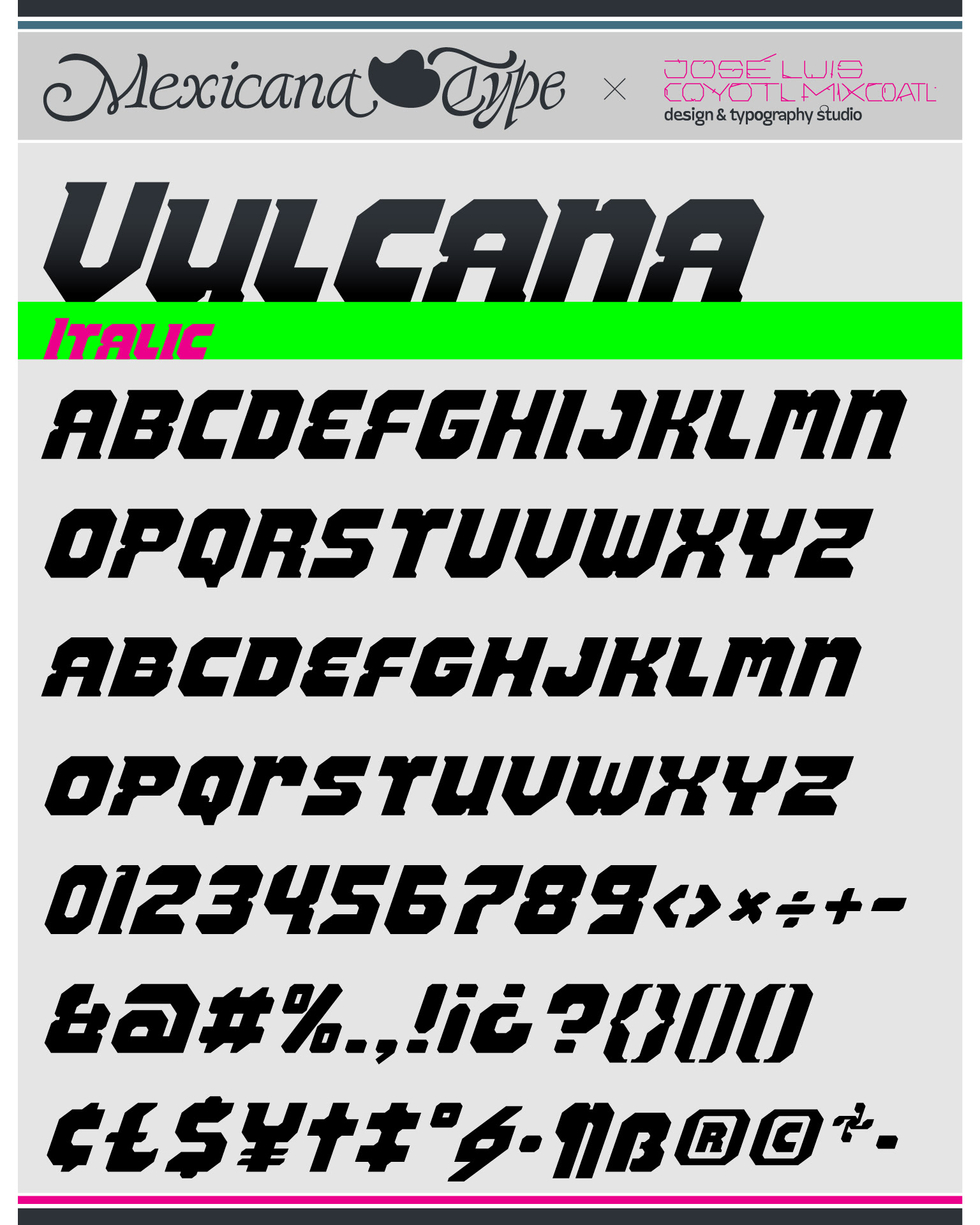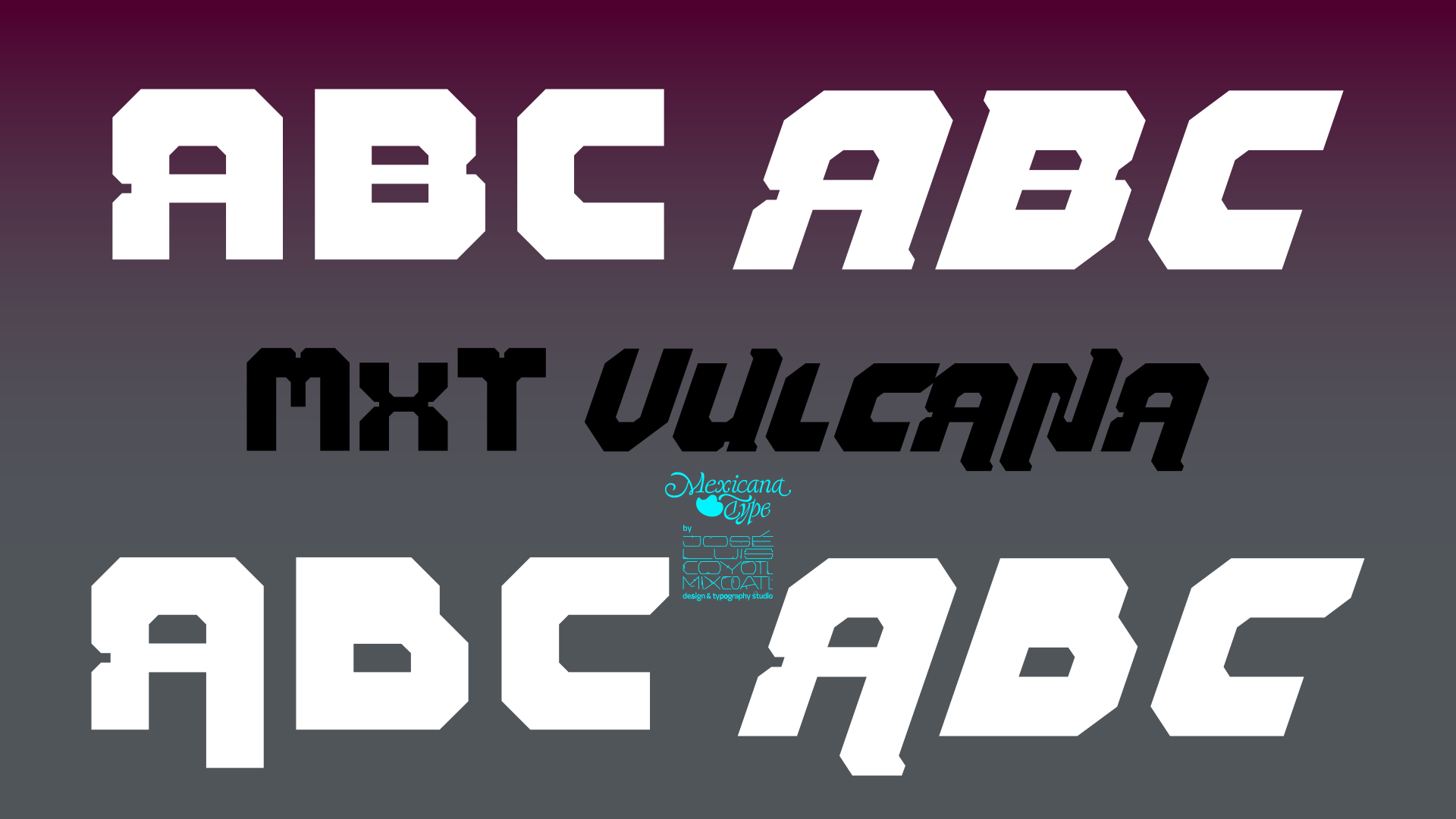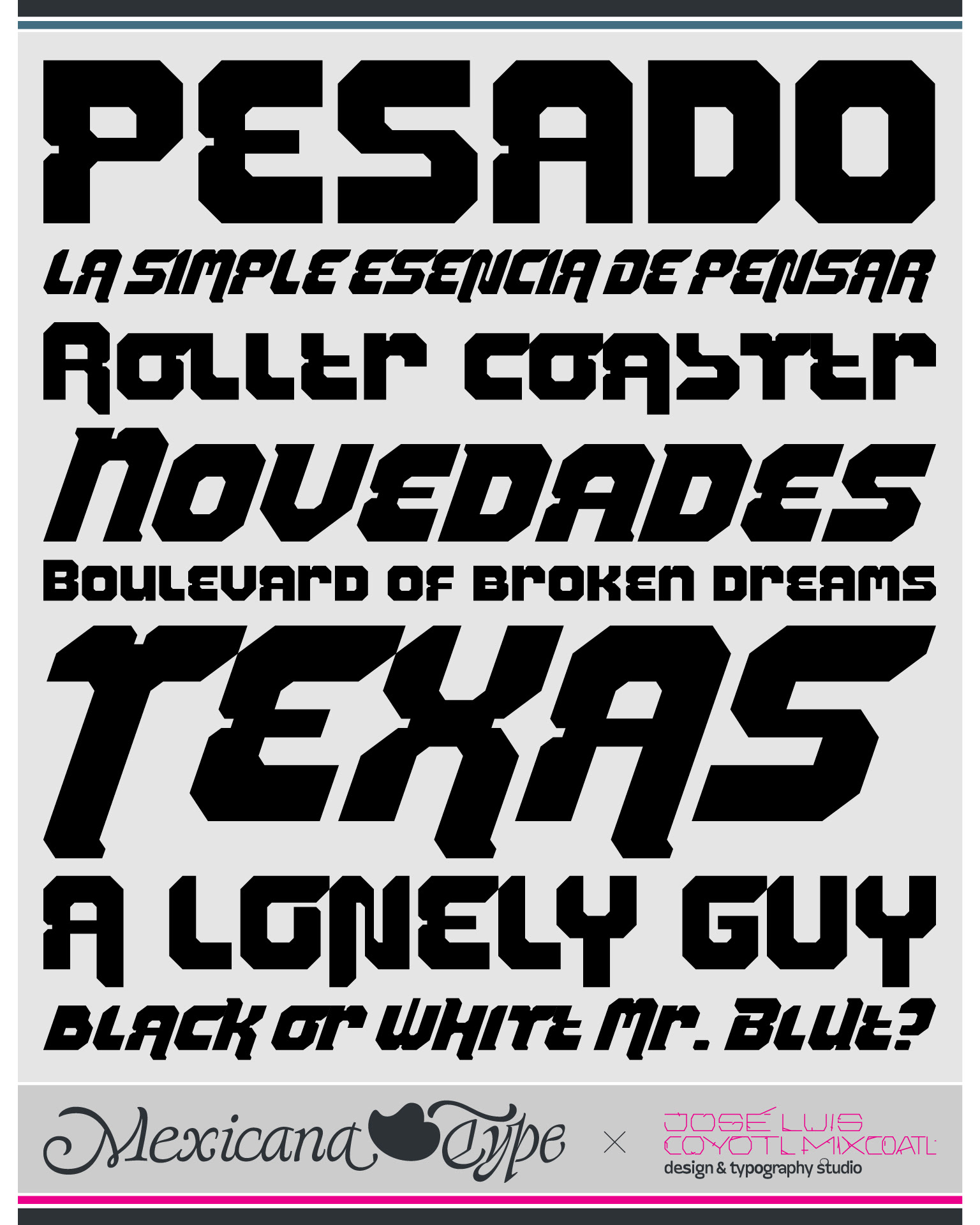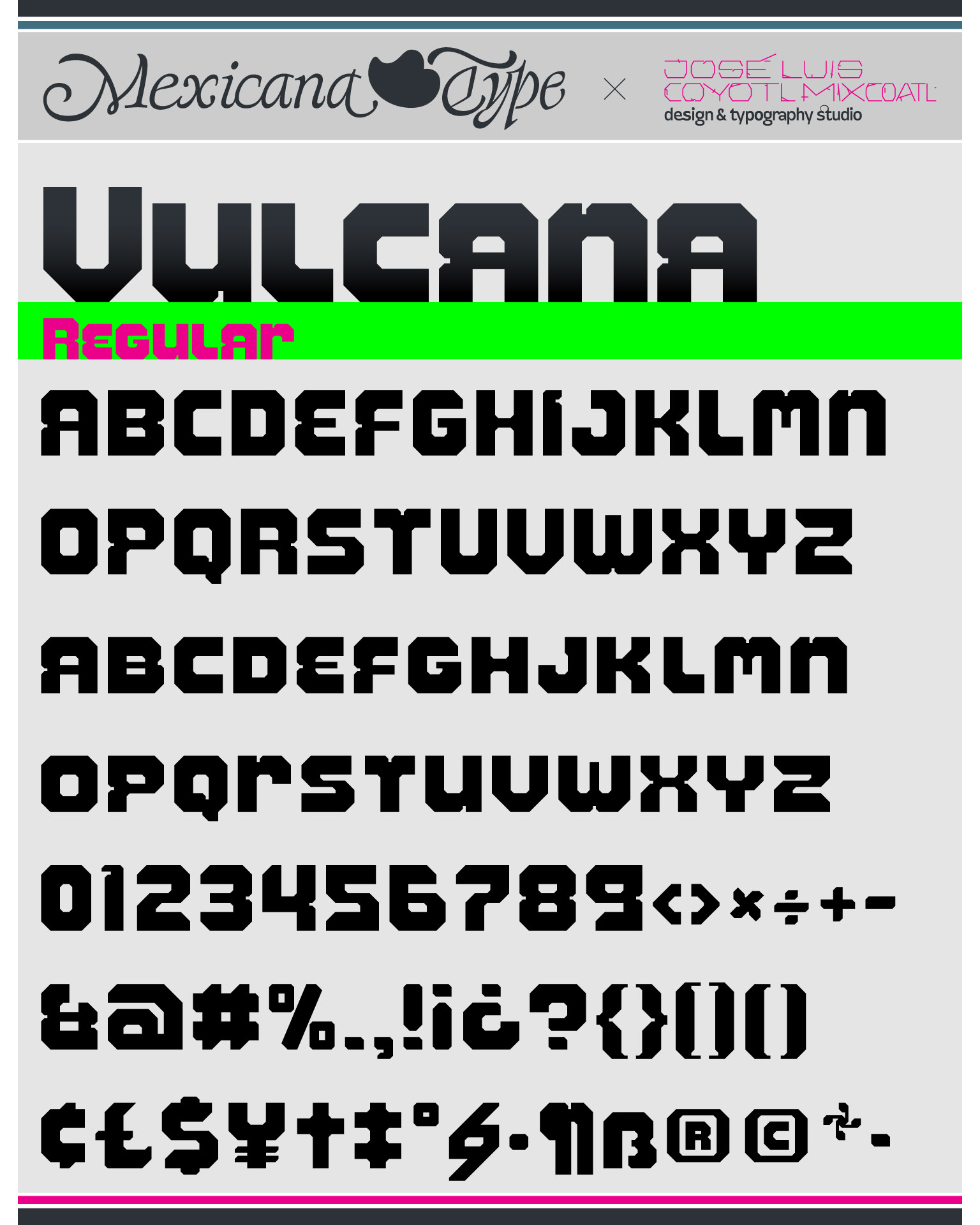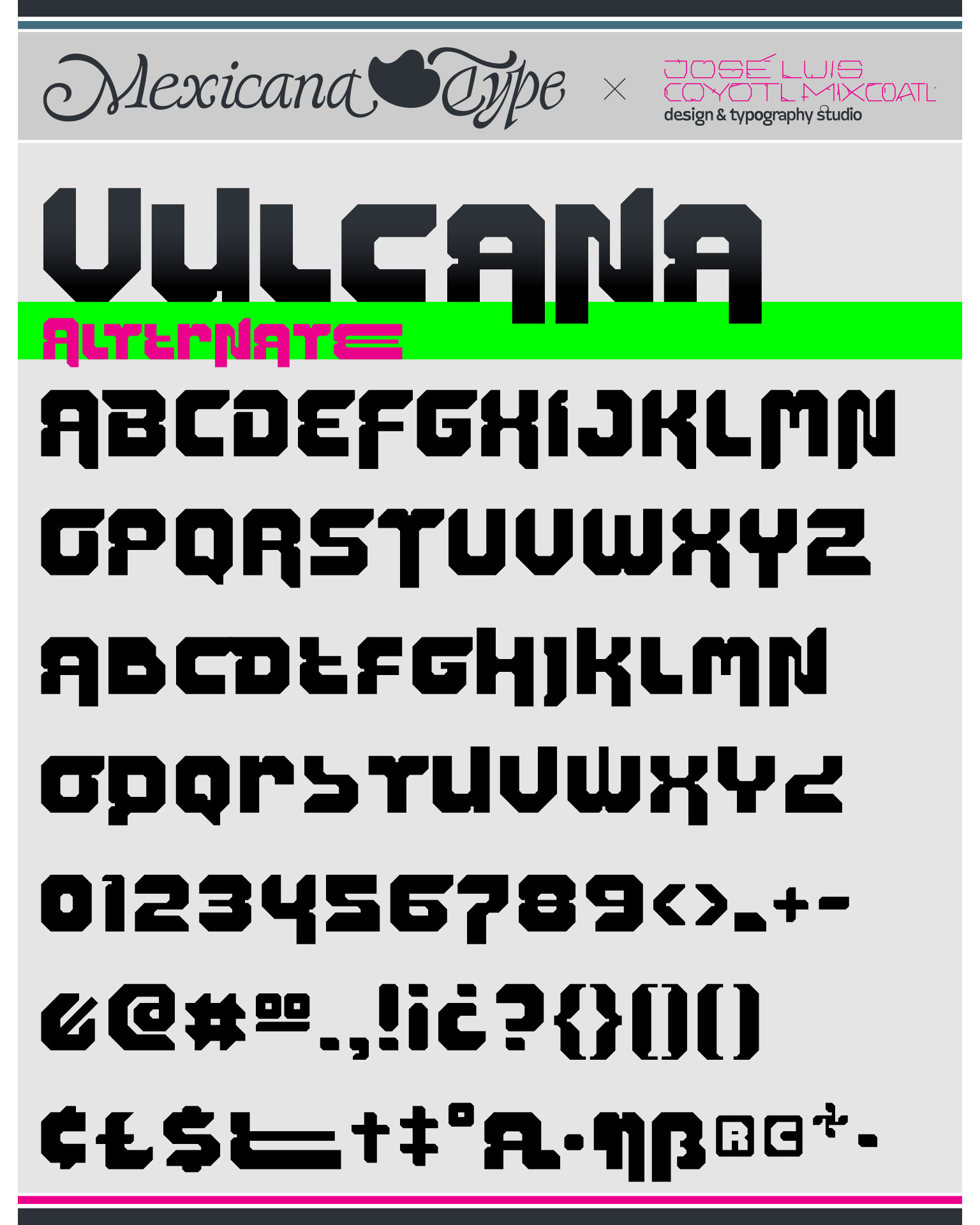
MxT Vulcana es una familia de 4 fuentes tipográficas influenciada por la estructura de las letras y los anuncios de talacherías y talleres mecánicos sobre llantas viejas, pintadas con brocha gruesa, con una clara reinterpretación y estética más techno.
Su cuadratura y cuerpo permite integrar algunos detalles a manera de muescas, además de cortes biselados, dándole un acento e imperfección en su forma de estructura casi unicase, lo que le permite ver líneas de texto sólidas con muchos acentos visuales, además de formas extendidas en sus variantes *Alternate, así como terminaciones, extensiones y caracteres alternos.